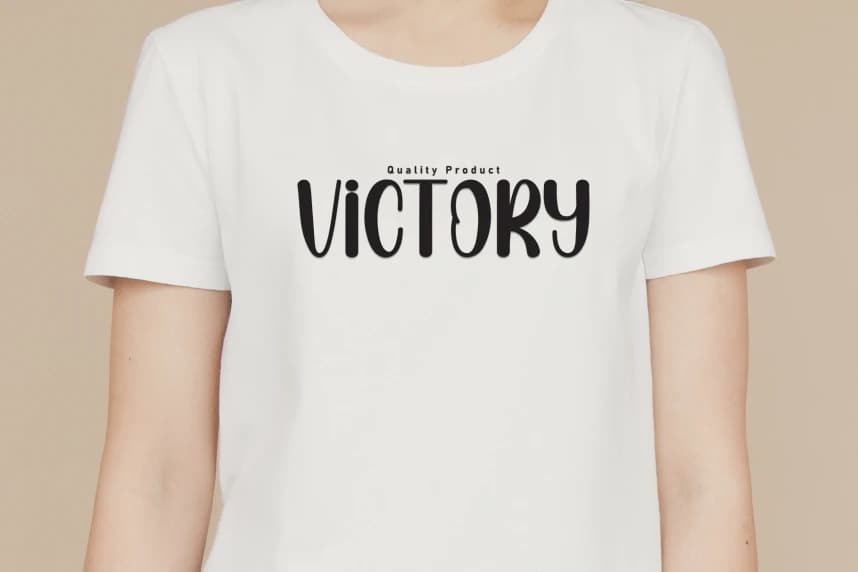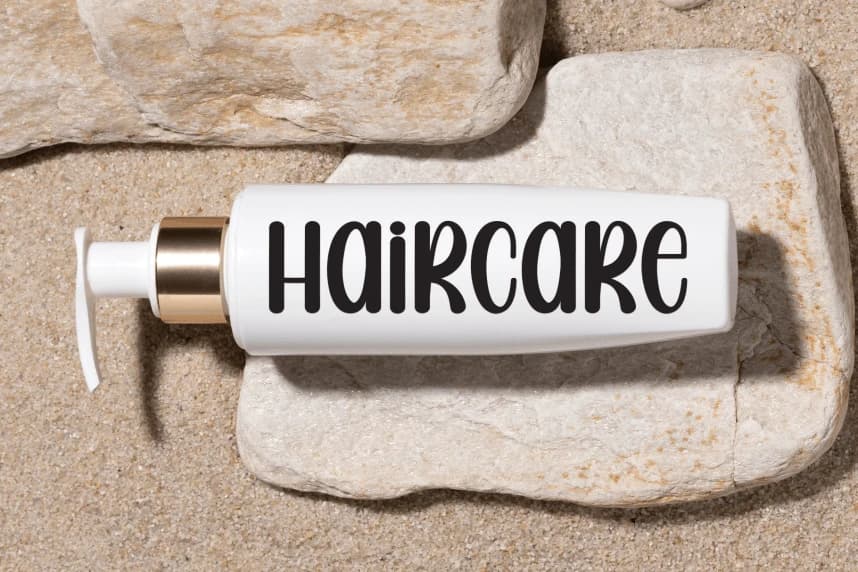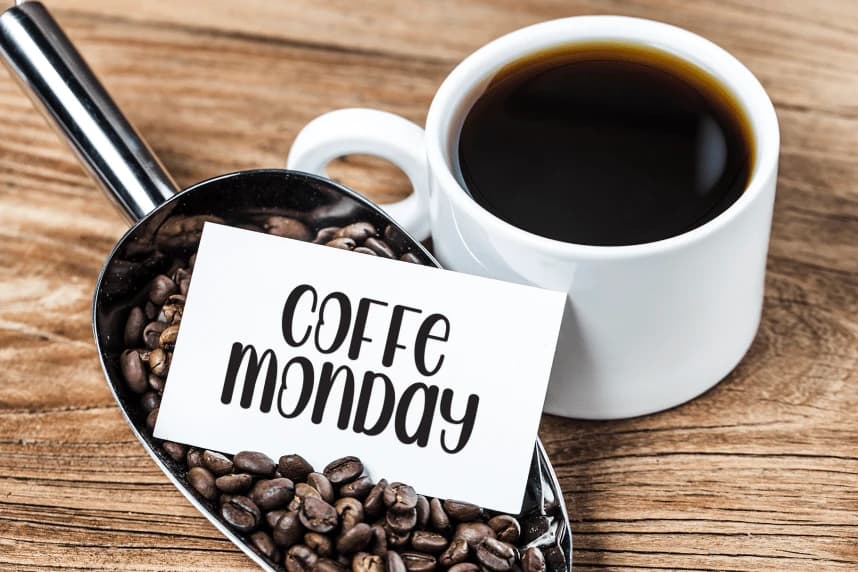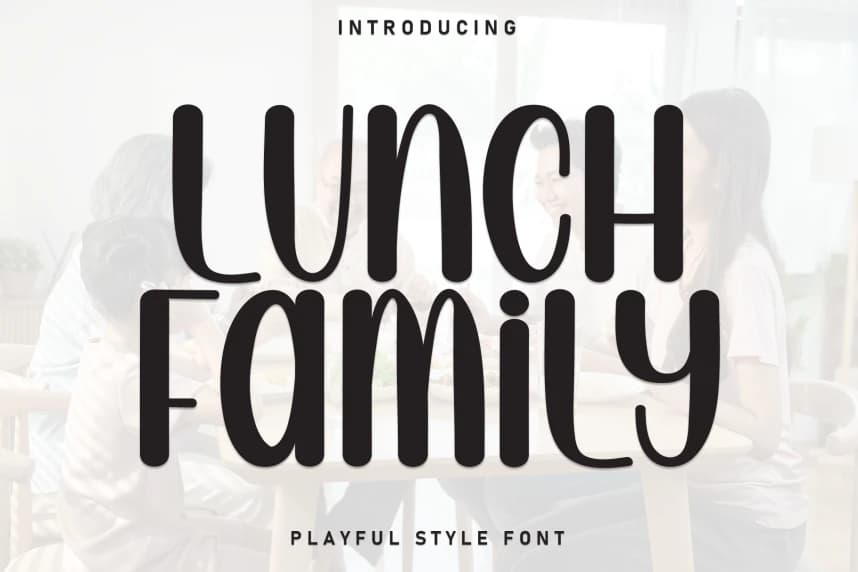
Lunch Family Playful Font
Lunch Family Playful Font, tatlı ve dostça bir el yazısı görünümlü gösterim yazı tipidir. Sevimli ve eğlenceli olan bu font, düğün davetiyeleri, kartlar için yazı yazarken ideal veya
Lunch Family Playful Font, tatlı ve arkadaş canlısı bir el yazısı gösterim fontudur. Şirin ve eğlenceli, bu font düğün davetiyelerini, kartları yazmak için idealdir, ya da